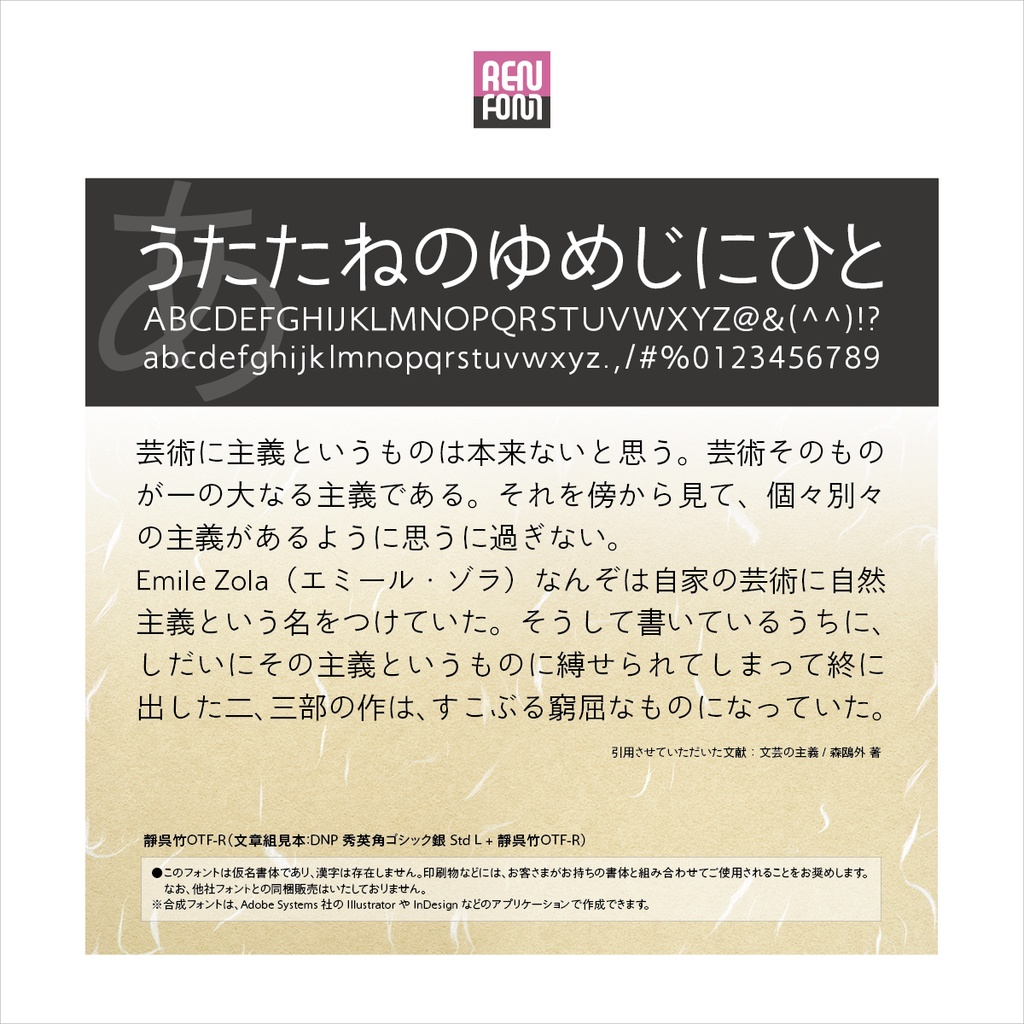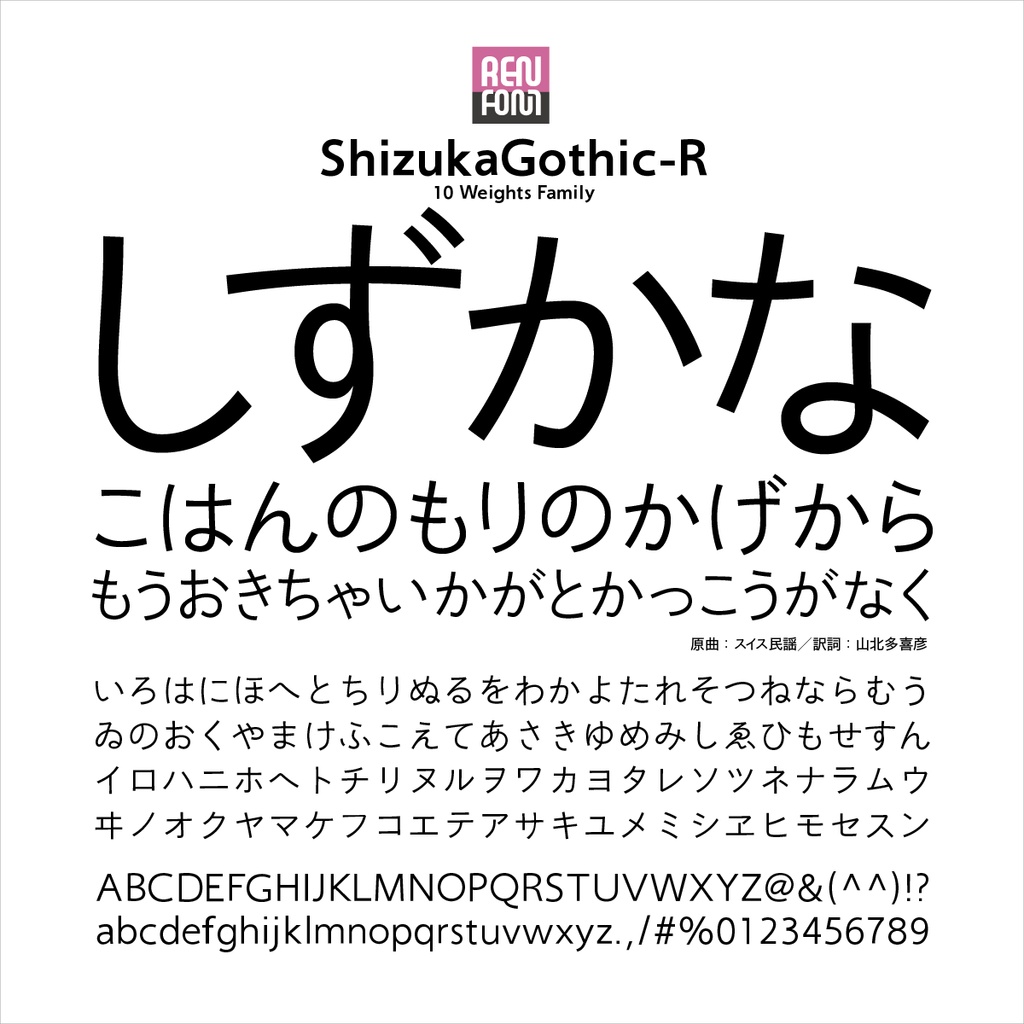
●ほんわかあたたかい書体 靜呉竹 OTF 10ウェイトファミリー / OpenType
特徴を極力抑え、“没個性”を追求しました。
靜呉竹ファミリーの各書体は、読むことに専念してもらうために開発しました。書体に特徴を盛りこんでしまうと、読むことの妨げになることがあります。 この書体は、それを避けることに主眼を置きました。究極の“没個性”、それが靜呉竹です。 ちょっとかしこまった普段使いの文字をフォントにしました。 勢いのある「勢蓮」とは何もかも対照的な控えめな書体。ゆえに「静(しずか)呉竹(ゴシック)」と名づけました。 「跳ね」「連綿」を極力抑えました。起筆部のアクセント(セリフ)もなくしています。 一画ずつ静かに、そして、ていねいな手書きにこだわりつつ、美しい伝統的書体寄りのフォルムに仕上げました。 本文組みに使ってみてください。ほんわかとした、あたたかく読みやすい文章になるはずです。 縦組み、横組みともプロポーショナル加工を加えています。また、横組みに限り(欧文も)、ペアカーニングもほどこしました。